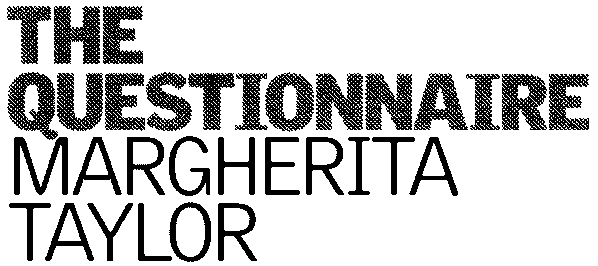
- Subject: Dear Weekend
Suite à un court séjour de l'autre côté de la Manche, je suis en mesure
d'affirmer qu'il est tout de même réconfortant de constater que certains
lecteurs de journaux anglais savent encore s'indigner pour une cause
typographique juste, et n'hésitent pas à apostropher le rédacteur en chef
pour lui faire connaître leur point de vue. Voici la reproduction de la
lettre qu'un certain Alan Rankin n'a pas craint d'envoyer au Gardian à
propos de son supplément de fin de semaine :
I generally enjoy reading Guardian Weekend, but two matters thoroughly
infuriate me: the caps typeface used for headlines appears to be sans serif,
except for the 'I', which alone is an annoyingly serified incongruity. Not
even a greengrocer would tolerate this. I need not mention the other
irritation, as you already receive plenty of complaints about her.
Traduction personnelle, pour ceux qui sont fâchés avec la langue de Tony
Blair :
D'une façon générale, j'aime bien lire le « Guardian Weekend », mais il y a
deux choses qui m'agacent prodigieusement : la police capitale utilisée pour
les titres semble être sans empattements, sauf le « I » qui à lui seul est
une ennuyeuse incongruité empattée. Même une marchande de quatre saisons
trouverait cela insupportable. Je n'ai pas besoin de mentionner l'autre
sujet d'irritation, vous recevez déjà suffisamment de plaintes la
concernant.
La dernière phrase fait allusion à Julie Burchill qui signe une chronique
hebdomadaire dans le journal, et fait effectivement l'objet d'autre lettres.
Il va de soi que la remarque typographique est rigoureusement exacte.
Je n'ai pas souvenir d'avoir jamais lu une lettre de ce genre dans un
journal français, mais je ne lis pas tout.
PS : « Dear Weekend », c'est le titre de la rubrique du courrier des
lecteurs du « Guardian Weekend ».